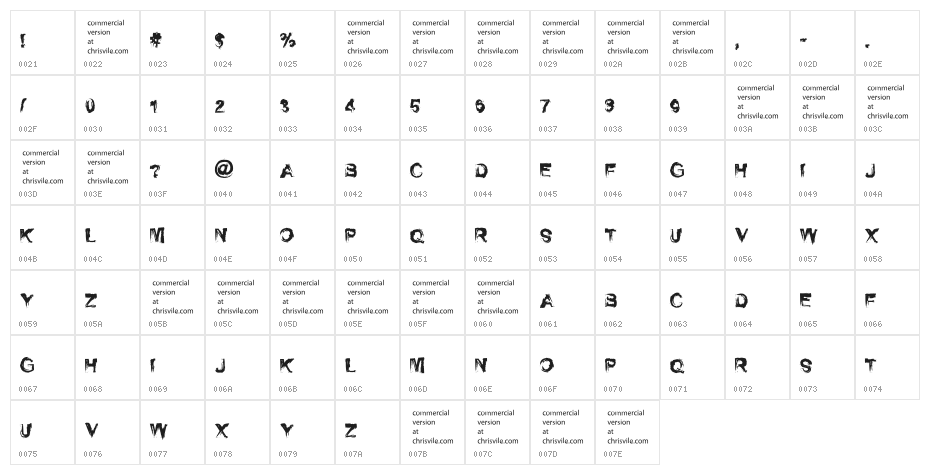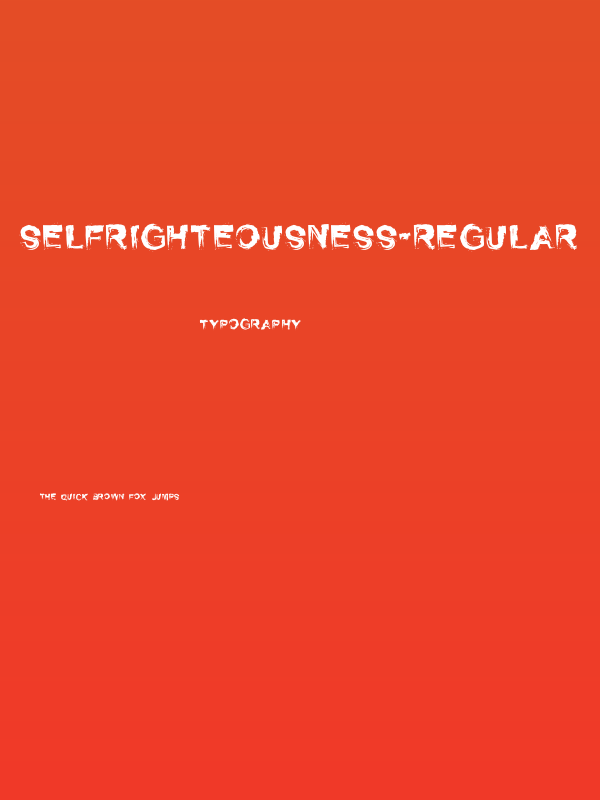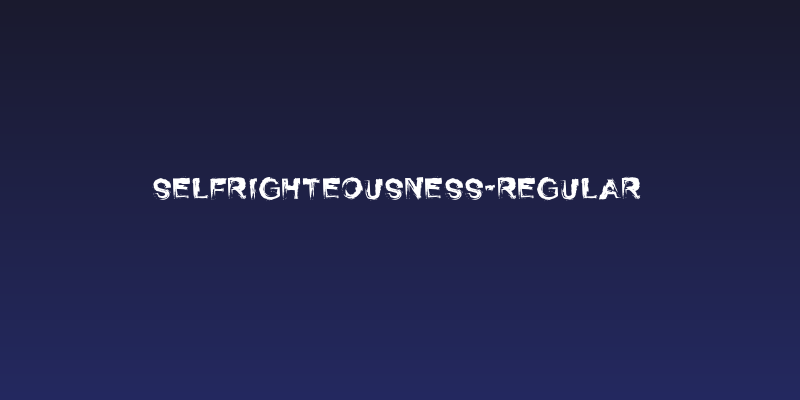
SelfRighteousness-Regular Font
| Gesamtstil | Grunge, Edgy, Distressed |
| Vorgeschlagene Projekte | Album covers, posters, urban-themed designs, rebellious branding. |